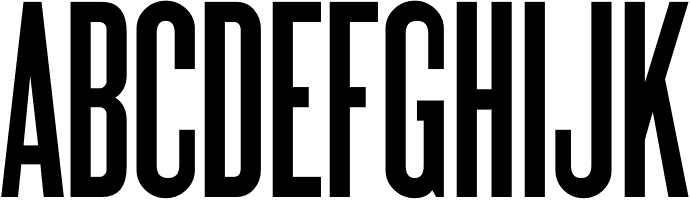
Kostenloses Pendant zu "Silvertone Woodtype"?
Ganz grob dran, mit stark abweichenden Kleinbuchstaben:
League Gothic von The League of Moveable Type, 4 Schnitte:
Steelfish von Typodermic, 7 Schnitte:
Gliscor Gothic von Ash Pikachu Font
Nur SmallCaps/AllCaps:
SF Movie Poster von ShyFonts, 8 Schnitte:
Gobold von 7NTypes:
Bebas Neue von Flat-it, 5 Schnitte: